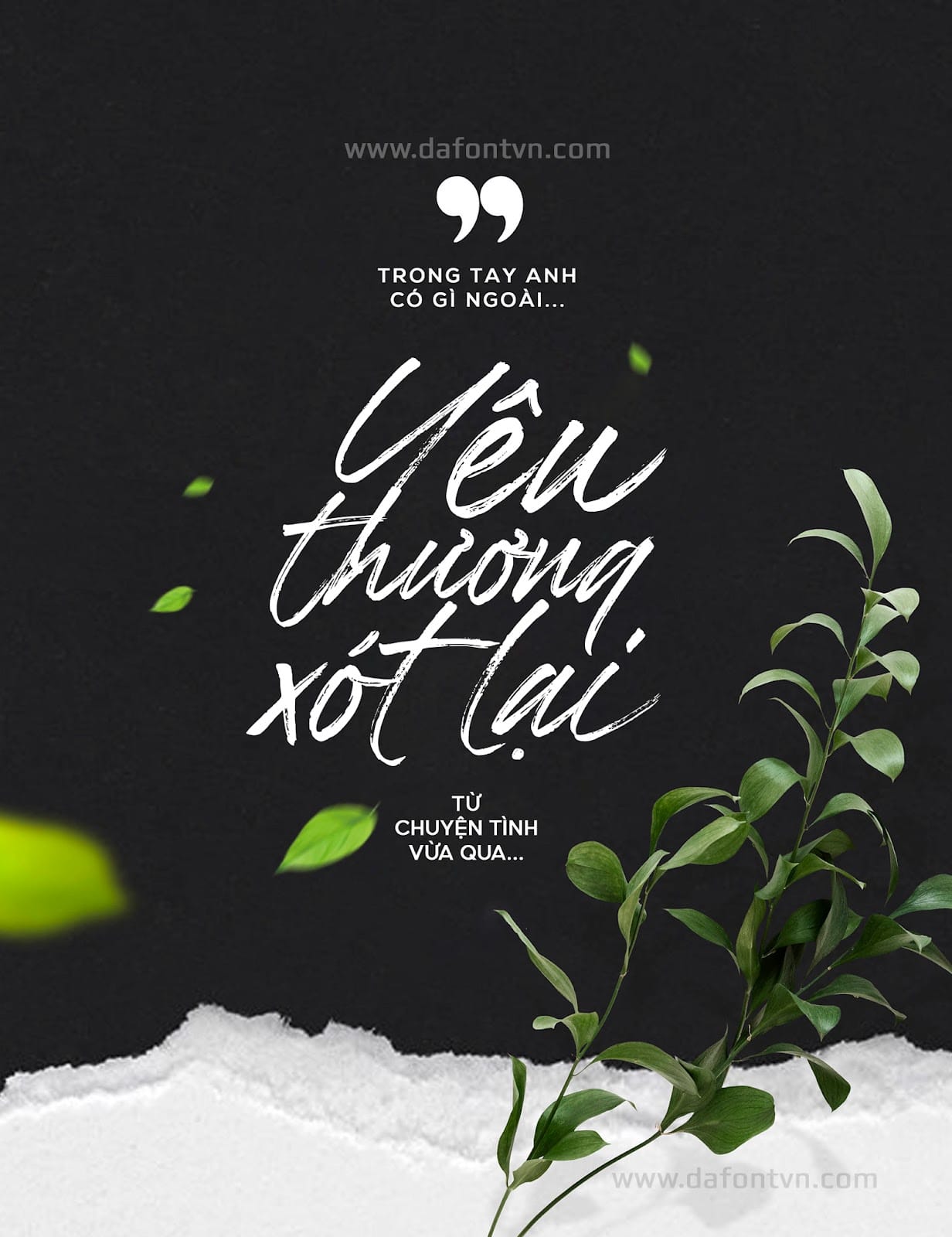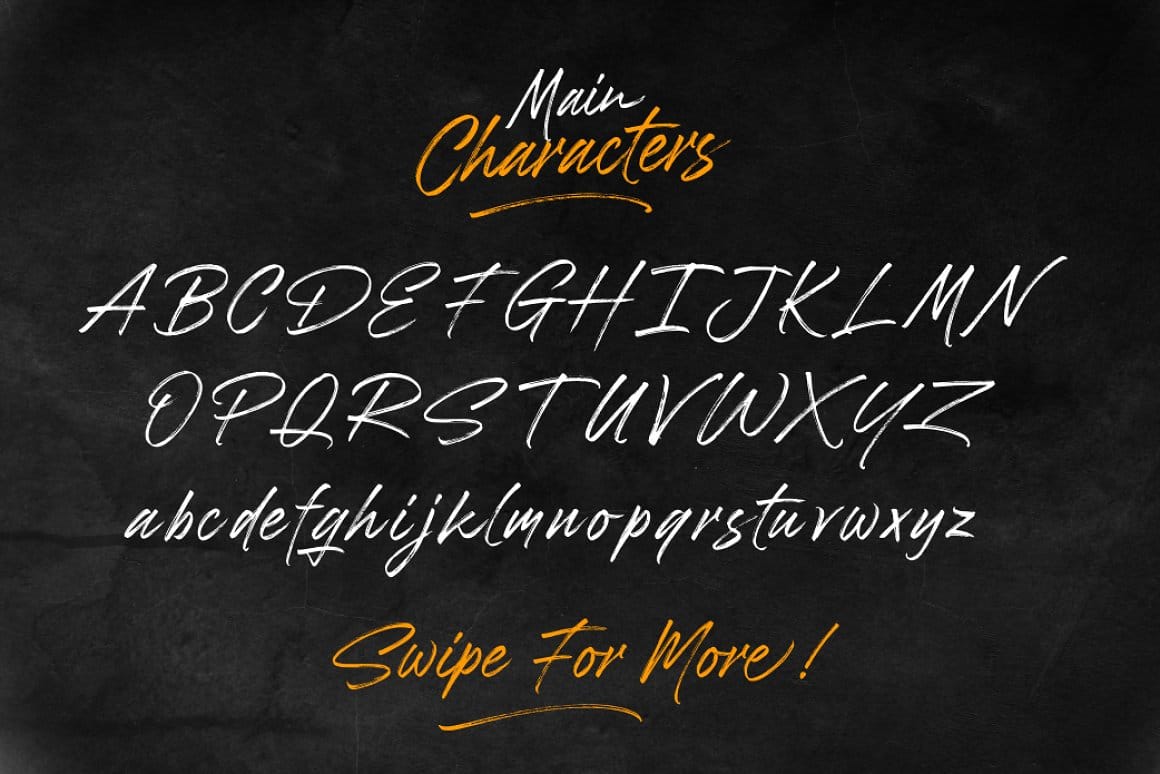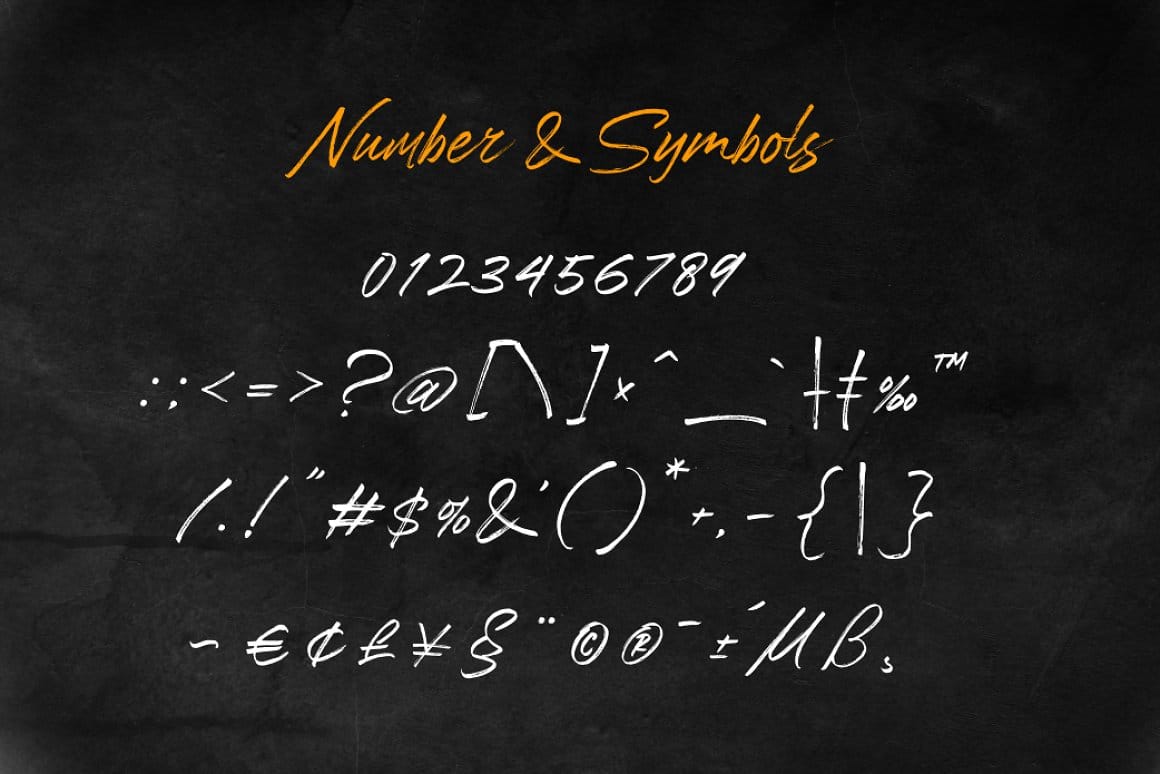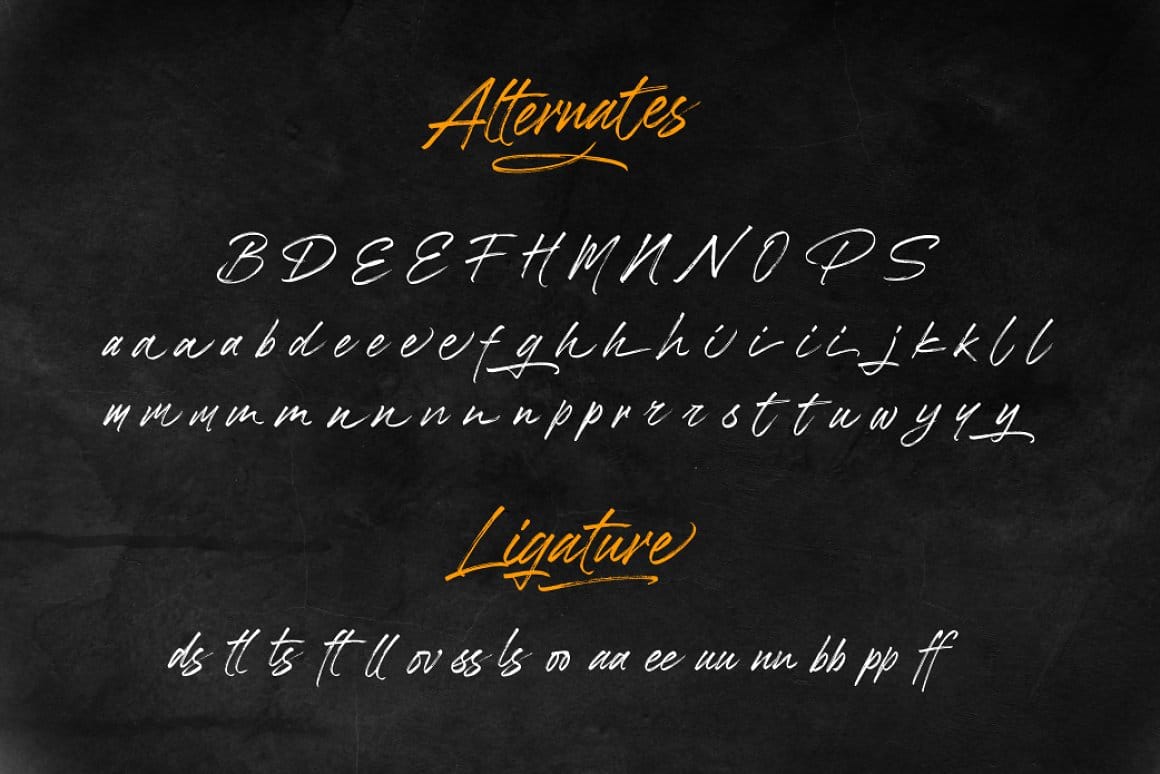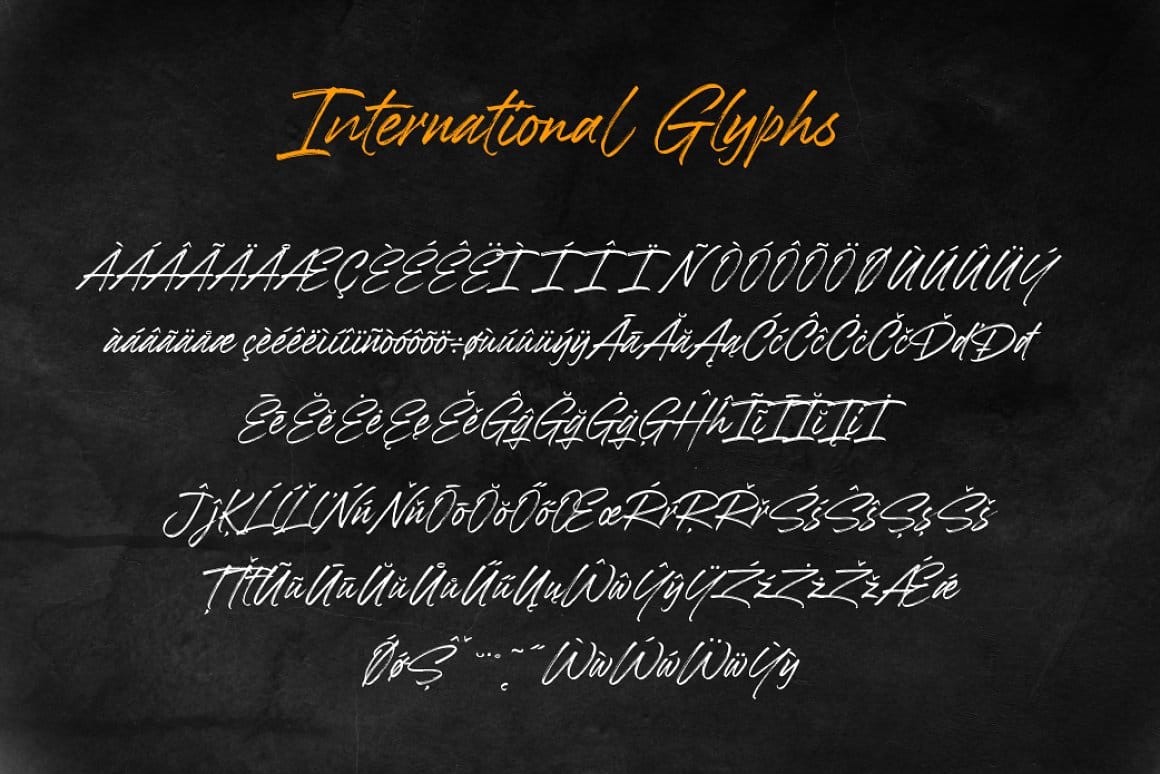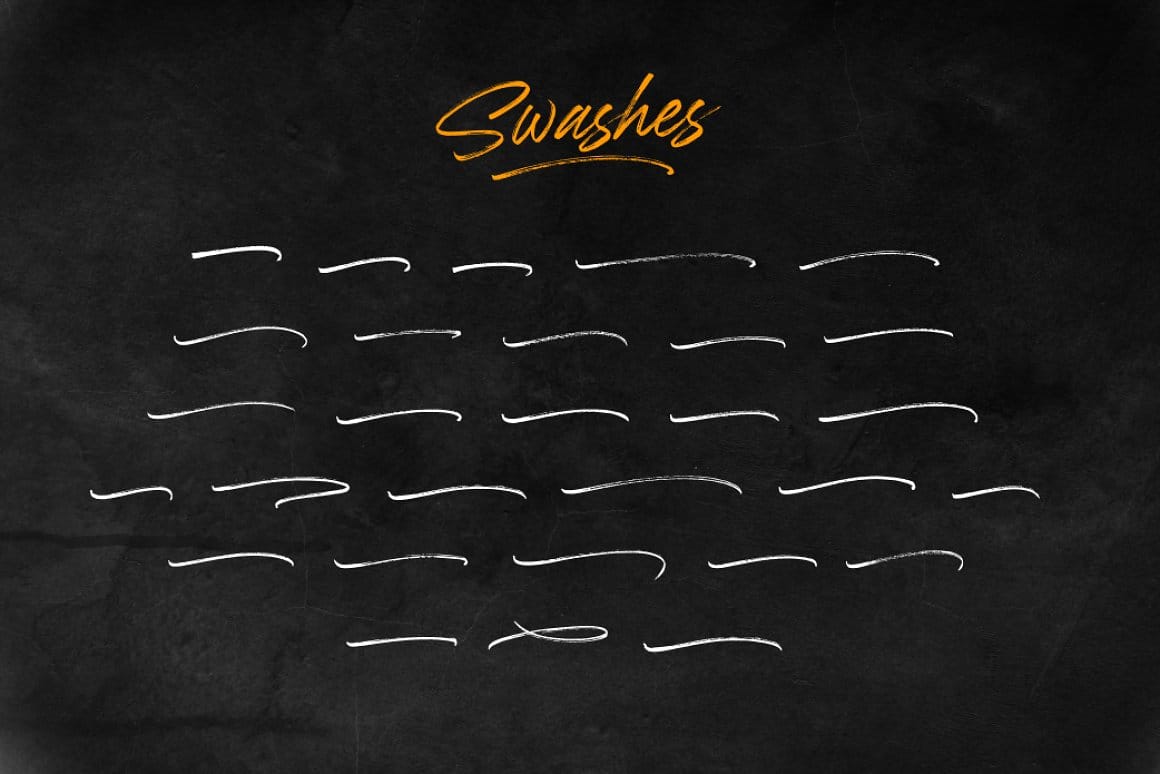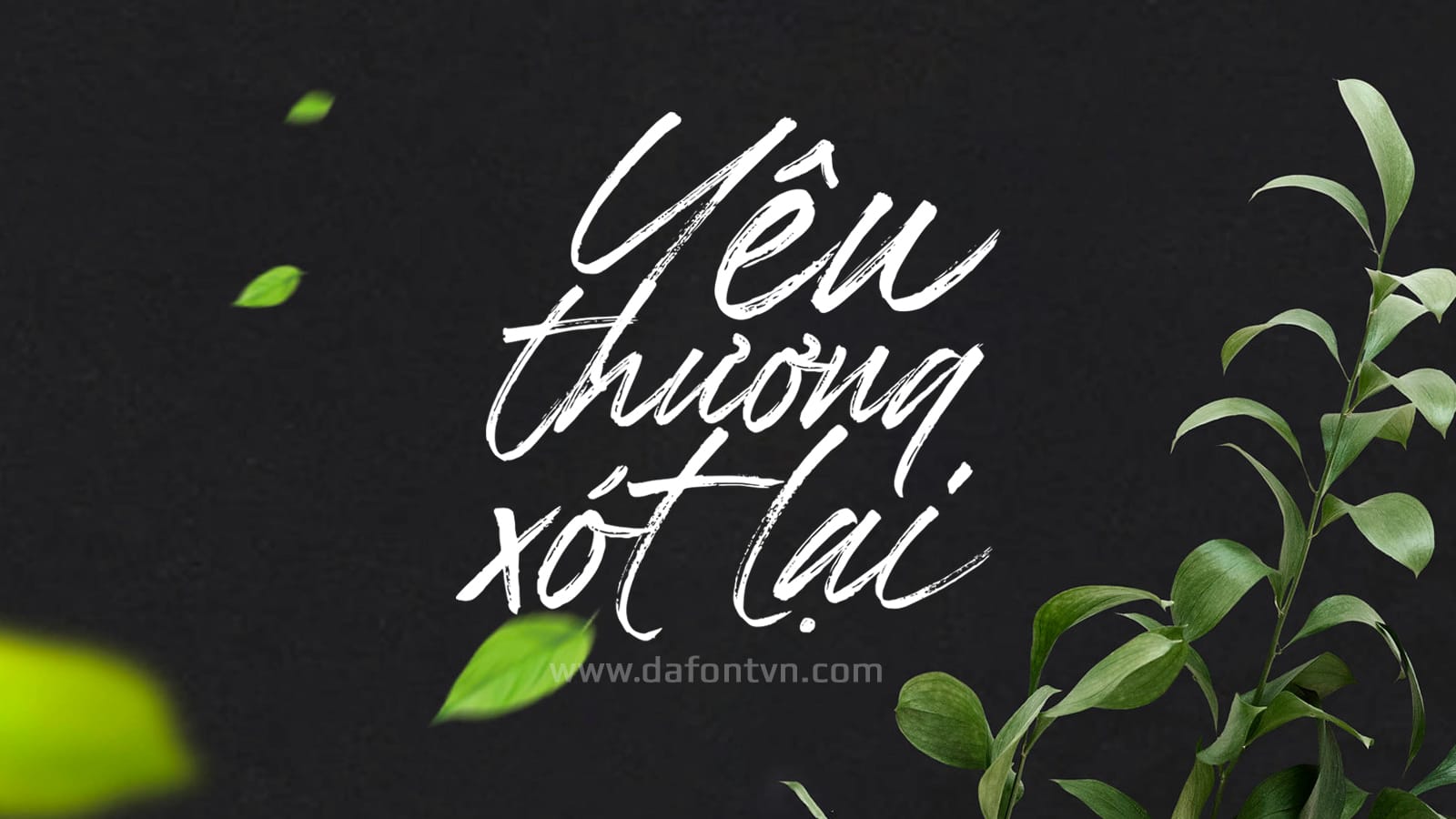
Font Brushwell Việt Hóa là một font brush khá đẹp được lấy cảm hứng từ những chữ bút lông, mang đến hiệu ứng bút lông để tạo ra vẻ tự nhiên của thư pháp bút lông viết tay.Font chữ này cũng được trang bị các tính năng OpenType tiêu chuẩn như Ligatures và Stylistic Set Alternates. Font được việt hóa đầy đủ, kerning, chỉnh sửa lại và tối ưu, việt hóa bởi NVN.